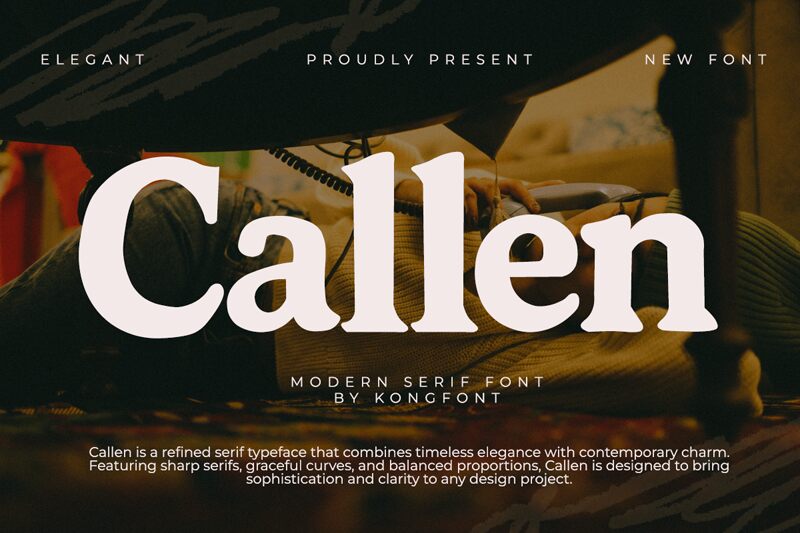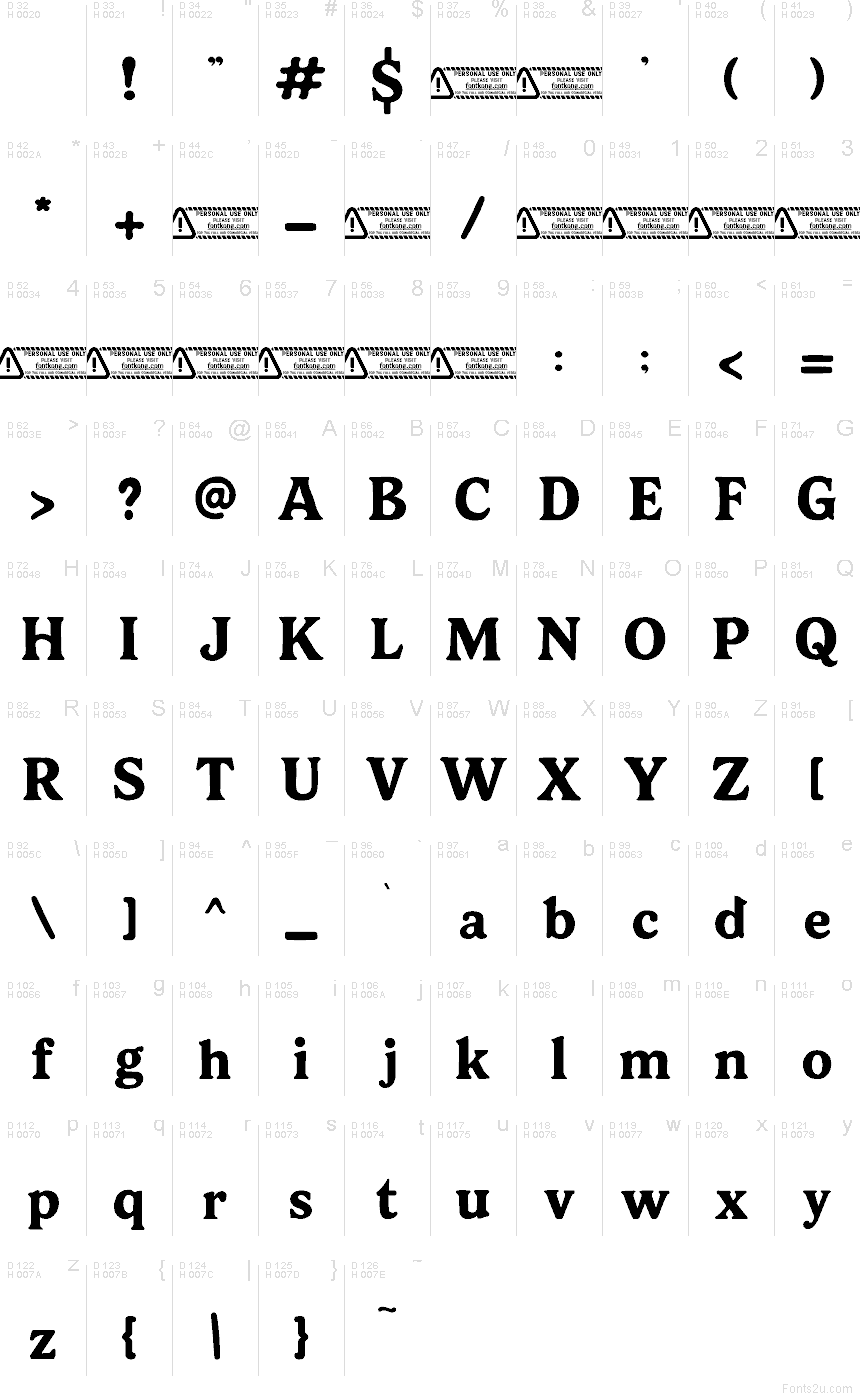
Callen von Kong Font ist eine kostenlose Old-Style-Serifenschrift mit einer ruhigen, literarischen Note und einer sanften, märchenhaften Wärme. Die Buchstaben kombinieren weiche, eingekerbte Serifen mit robusten Vertikalen und abgerundeten Formen, wodurch die Schrift eher bodenständig und traditionell als scharf oder formell wirkt.
Sie eignet sich hervorragend für Buchcover, Café-Branding, redaktionelle Überschriften, Einladungen und Verpackungen, bei denen ein klassischer, aber dennoch nahbarer Look gefragt ist. Als kostenlose Schrift macht Callen besonders in kurzen Überschriften, Logo-Schriftzügen und Initialen eine gute Figur, da ihre breiten Kurven und sanft gearbeiteten Serifen selbst wenigen Buchstaben eine harmonische Präsenz verleihen.